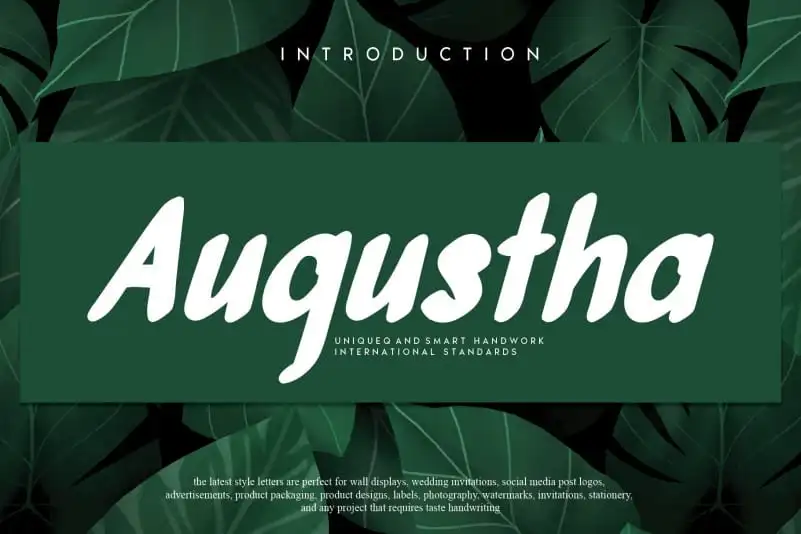
A Augustha Display Font é uma seleção única de letras para quem busca um toque autêntico em projetos visuais criativos. Com seu design elegante e detalhado, ela oferece uma experiência singular para designers gráficos e artistas digitais que buscam personalidade para suas obras. Especialmente adaptada para aplicar no estilo de mídia social ou para criar texturas efeitos interessantes em designs web, a Augustha Display Font é perfeita para quem busca qualidade e originalidade na sua fonte escolhida. Inspirada nas antigas tipografias clássicas, mas com um toque contemporâneo que se adapta a vários estilos, esta fonte é ideal tanto para aplicativos como para impressão digital. Em uma era onde as opções de fontes são inúmeras, a Augustha Display Font se destaca por oferecer uma experiência visual única e memorável aos seus usuários.